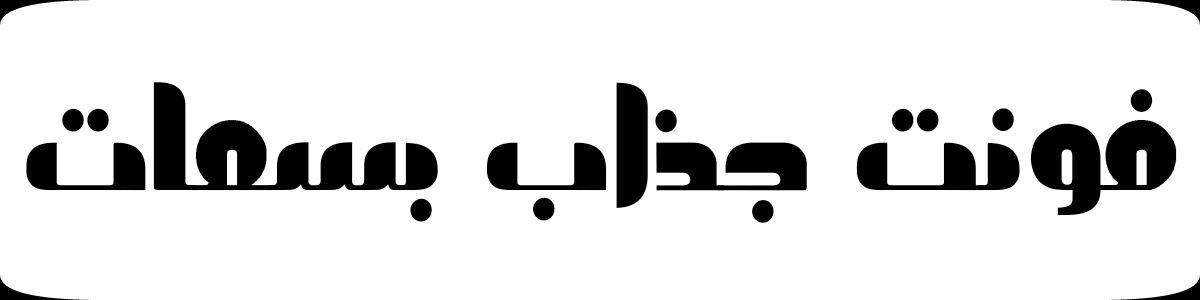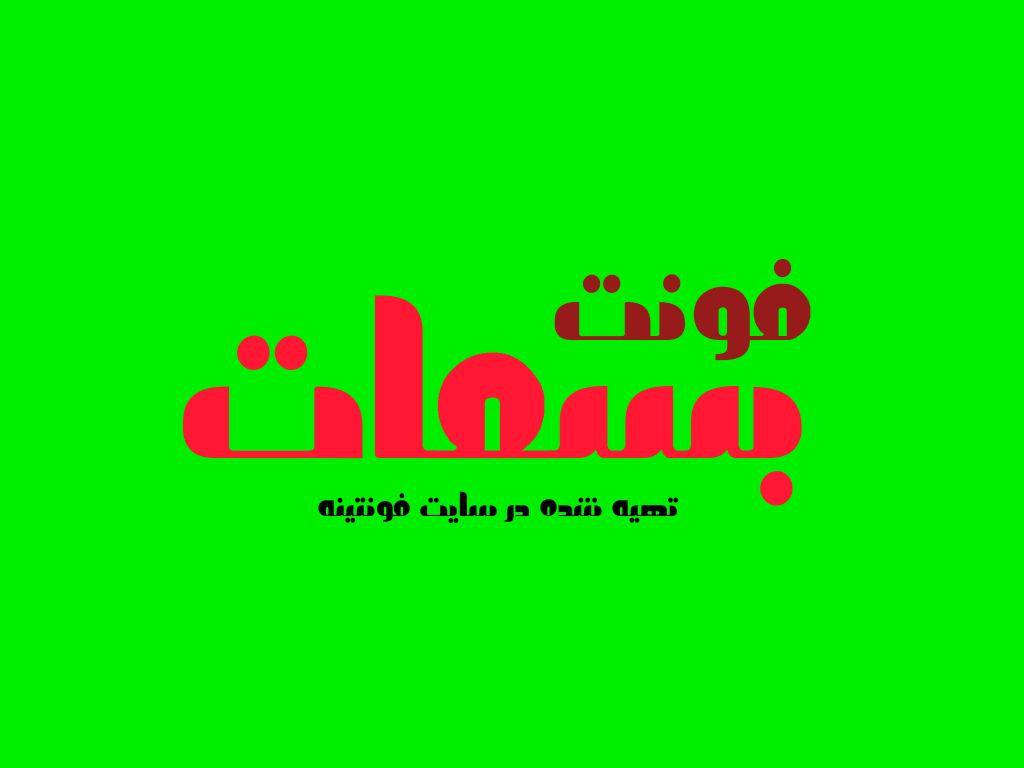
دانلود فونت بسمات در خدمت شما بزرگورارن هستیم با ارائه فونت زیبا و فارسی بسمات این فونت برای طراحی های لوگو و بنر و…. مورد استفاده قرار میگیرد.
تصاویری زیبا از طراحی های خاص با فونت بسمات که برای نمایش و نمونه پیش فرضی از نمایش این فونت کاربردی طراحی شده است